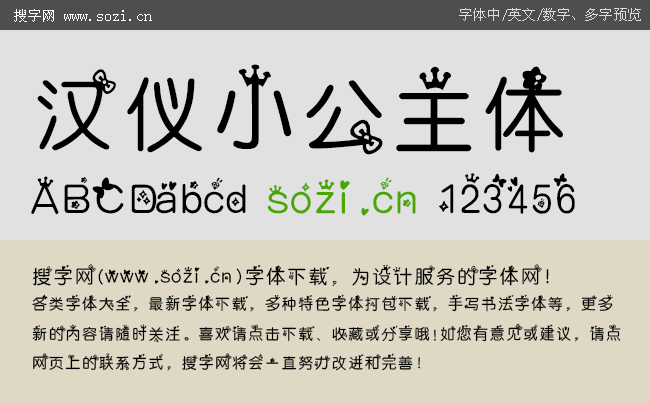
漢儀小公主體
搜字網(wǎng)給大家提供一款漢儀小公主體手機(jī)中文字體下載。這款手機(jī)字體是在圓體字體筆畫間插入了可愛(ài)的卡通圖案。在具備圓字體清晰端正的風(fēng)格同時(shí),卡通味也特別濃,是一款非常可愛(ài)的卡通字體,特別適合喜歡手機(jī)字體個(gè)性一些的朋友在手機(jī)上安裝使用。